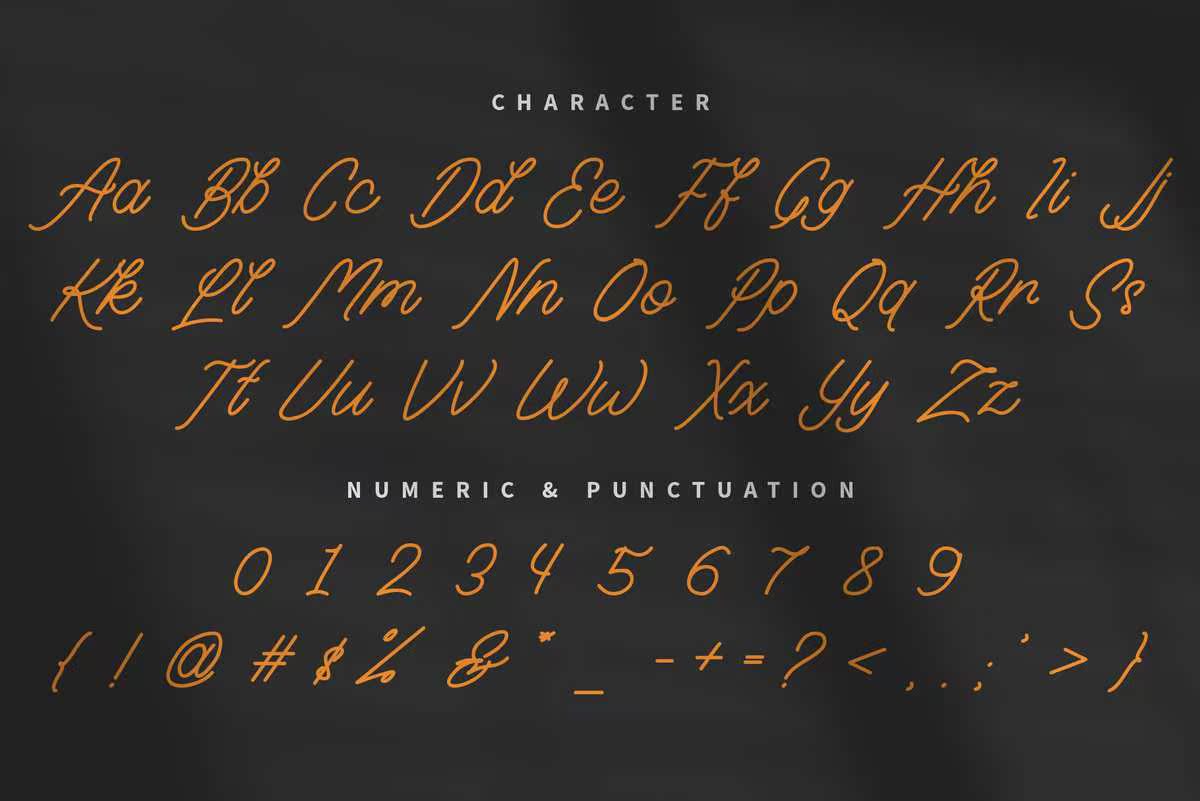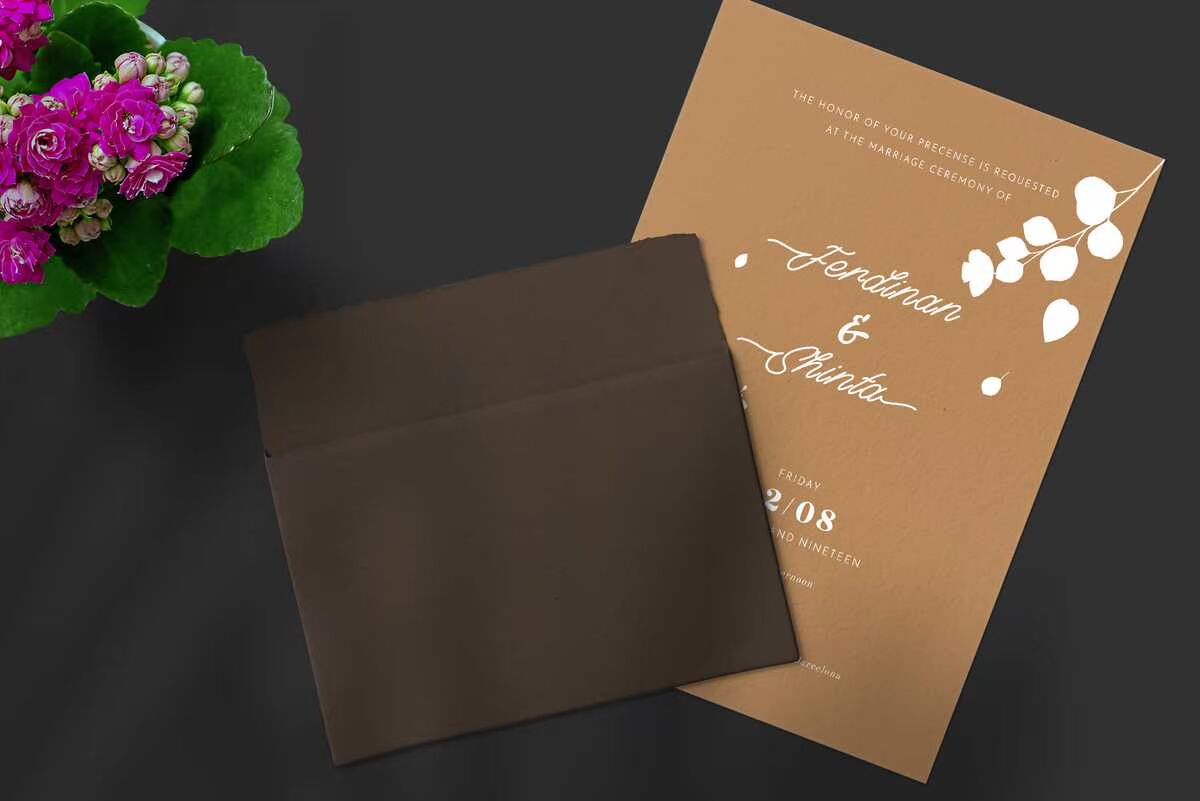
Saturday Font带有手写体Tenstyles。文字和数字的集合适用于您的项目的标识、品牌设计、标识设计、数字刻字艺术、T恤/服装、海报、杂志、标志、广告设计和任何设计需求。Saturday Font带有手写体Tenstyles。文字和数字的集合适用于您的项目的标识,品牌设计、标志设计、数字文字艺术、T恤/服装、海报、杂志、标志、广告设计和任何设计需求。